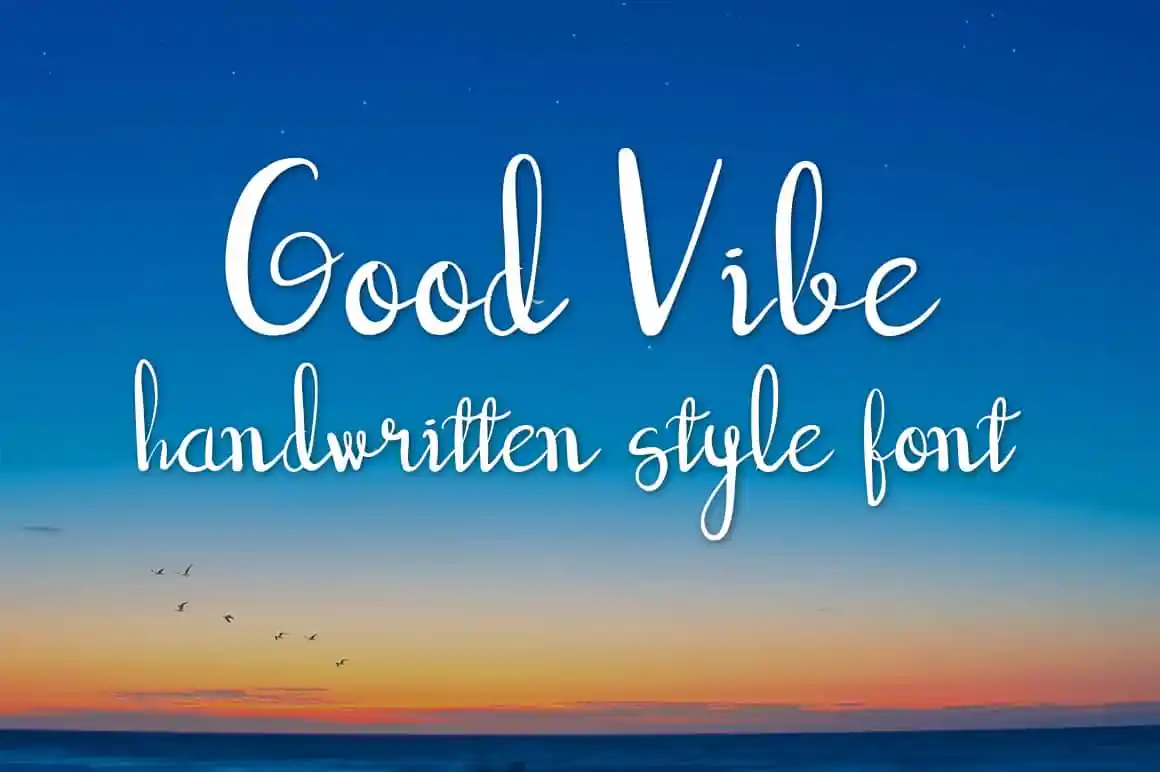
Good Vibe Script Font – Download Grátis
A Good Vibe Script Font é uma escolha perfeita para quem busca algo elegante mas com um toque autêntico e natural. Esta nova tipografia moderna mantém a sofisticação do script enquanto adota uma mão-dura, conferindo-lhe um aspecto único e original que se torna perfeito em projetos variados. Suas formas delicadas combinam tão bem com elementos florais em cartões de convite para casamentos ou em banners, criando uma atmosfera romântica e envolvente. A Good Vibe também é ideal para personal branding, permitindo que você se destaque de maneiras originais e memoráveis. Seja você um designer ou criativo independente, a fonte Good Vibe tem muito a oferecer em termos de flexibilidade e originalidade. Escolha-a para transformar suas ideias em realidade com um toque único e inconfundível.